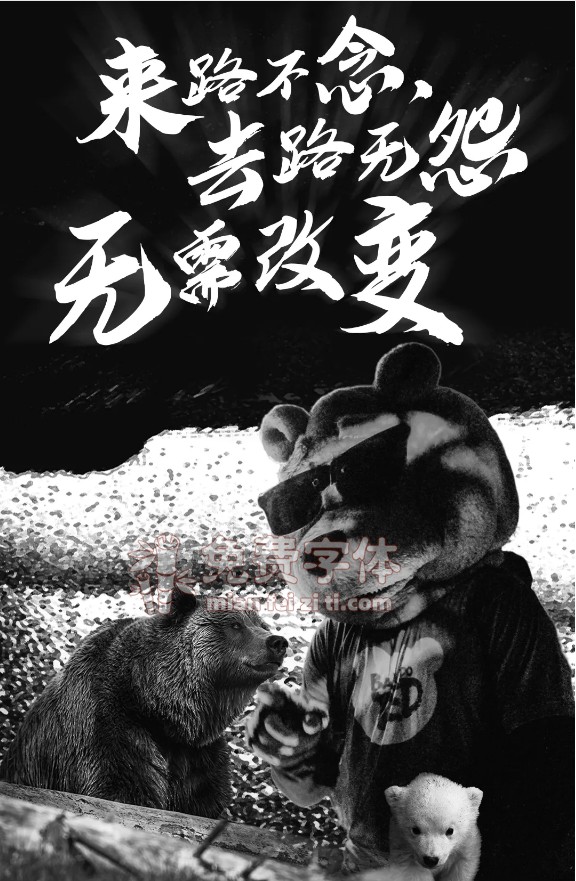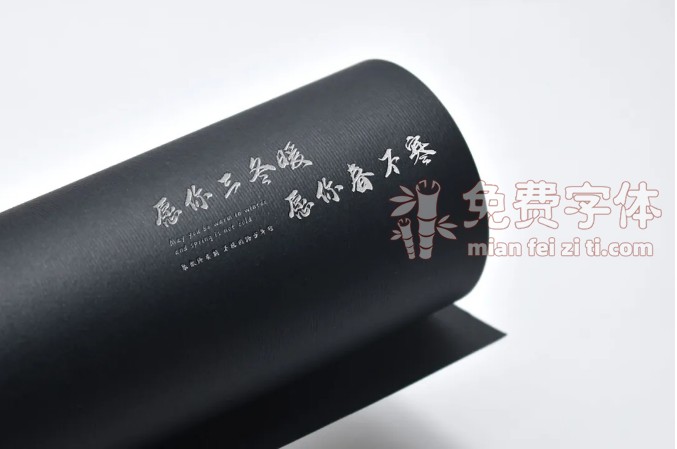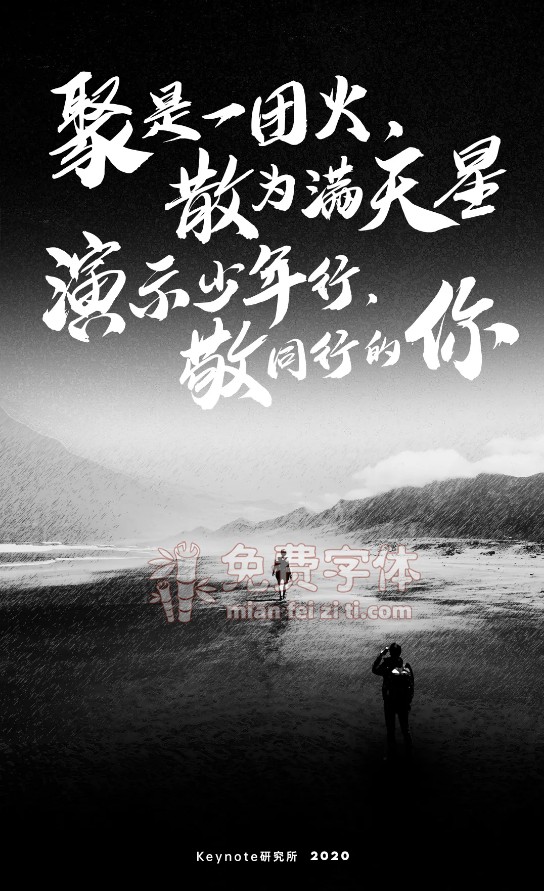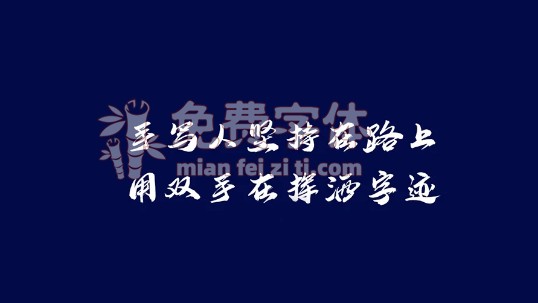
聚散终有期,不枉同路少年行《演示少年行》字体全新来袭字体资讯
你好,这里是 Keynote研究所,
我是人生哥。
一名不务正业的 PPT Designer!
有幸再次,与你见字如面!
做字是长期主义者
最好的诠释
学如逆水行舟,
这世间所有的事儿,
都源自匠心起笔时间作答!
从最初结识字体到今天拥有近十款字体!
用了两年的时间!
期间失去很多却也收获颇丰!
虽常感枯燥但仍可自得其乐!
直到今天,我也依旧认为,
只刚刚摸到了做字的门槛!
甚至还没完成一款标准字!
但这并不影响我继续做下去!
毕竟造字者,一字即是一生!
所幸《汉楷书刻体》已经在路上了!
抬头所望,皆为希望
过去的一年,
演示系列字体受到了很多人的喜爱。
字体是幻灯片的必需品!
特别是手书字体,
已经成为辅助演讲者情绪传递的核心要素!
所以今天发出的这套字体,
希望依旧可以对你有所帮助。
你的下一份幻灯片它来守护!
名曰:《演示少年行》
既从江湖来,便往江湖去!
聚是一团火,散为满天星!
聚散终有期,不枉同路少年行!
字体起源:
这套字体曾被他尘封三年之久,是回归自我的表达,笔划随性无章亦无法,皆因平凡最可贵!希望这套不平凡的字体可以走进你的视野,敬每一位愿不负青春且同行的少年!
做字不像做幻灯片,没有那么多花哨的技巧可供炫技,仅有黑白两色,却内谙乾坤!设计者的性格、秉赋、习惯,都藏在每一个文字中!一撇一捺皆风骨!造字这两年所言所听,声量不一。现在回头看去:
喜欢你的依旧会喜欢,
憎恶你的依旧不讨喜!
说那么多情怀和废话其实没什么用!